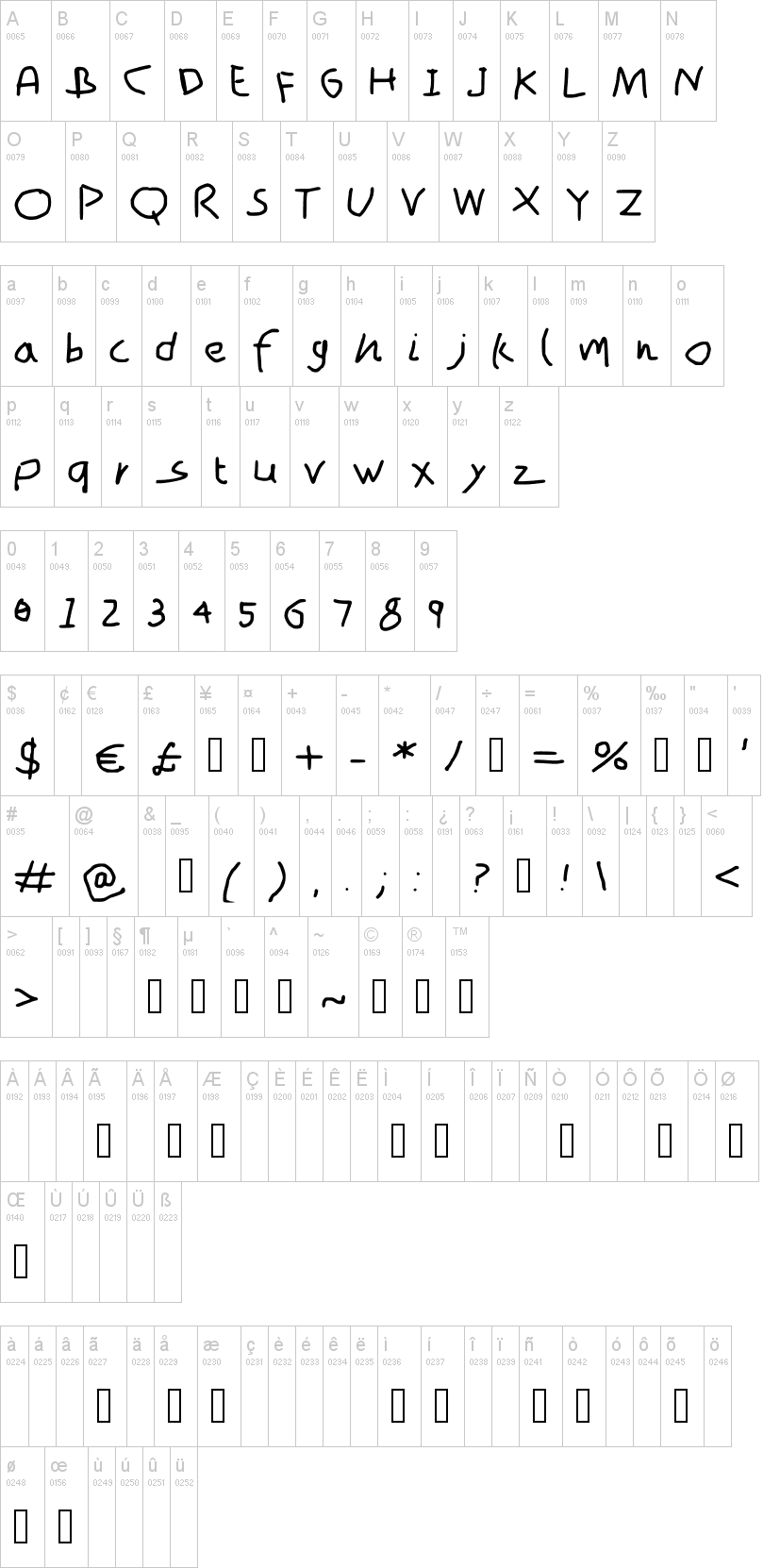
SamT字体是一种优雅、现代的无衬线字体,由字体设计师Sam Parrett于2017年发布。该字体具有流畅的线条和大胆的特点,适用于品牌设计、标志设计、海报、包装设计、印刷品和数字项目等各种场合。 SamT字体有两个不同的样式:正常样式和粗体样式,可用于不同的设计需求。这个字体家族中有多种字重和样式,包括常规、粗体、斜体、粗斜体等。 SamT字体的特点是类似于手写字体,但又充满了现代感。其特有的风格和视觉效果使其成为一种非常受欢迎的字体,广泛应用于设计行业。内容介绍
SamT是一款非常不错的手写艺术字体,具有很好的视觉感,适合于文化类的宣传设计、商业类品牌的广告和产品包装设计以及个性化文字排版等较多场景。